Il piacere di scrivere a mano
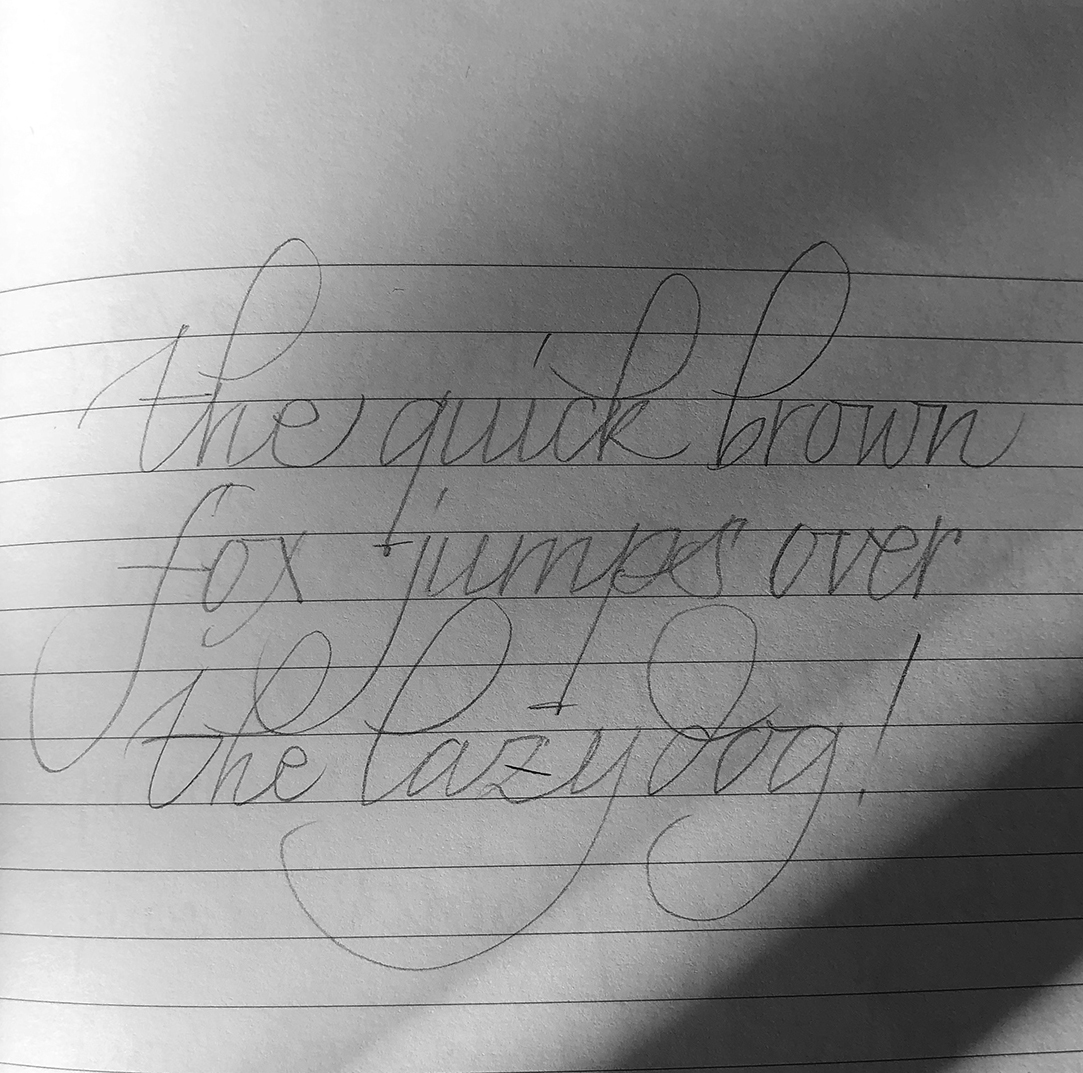
Il piacere di scrivere a mano
Calligrafia con Juls Criveller
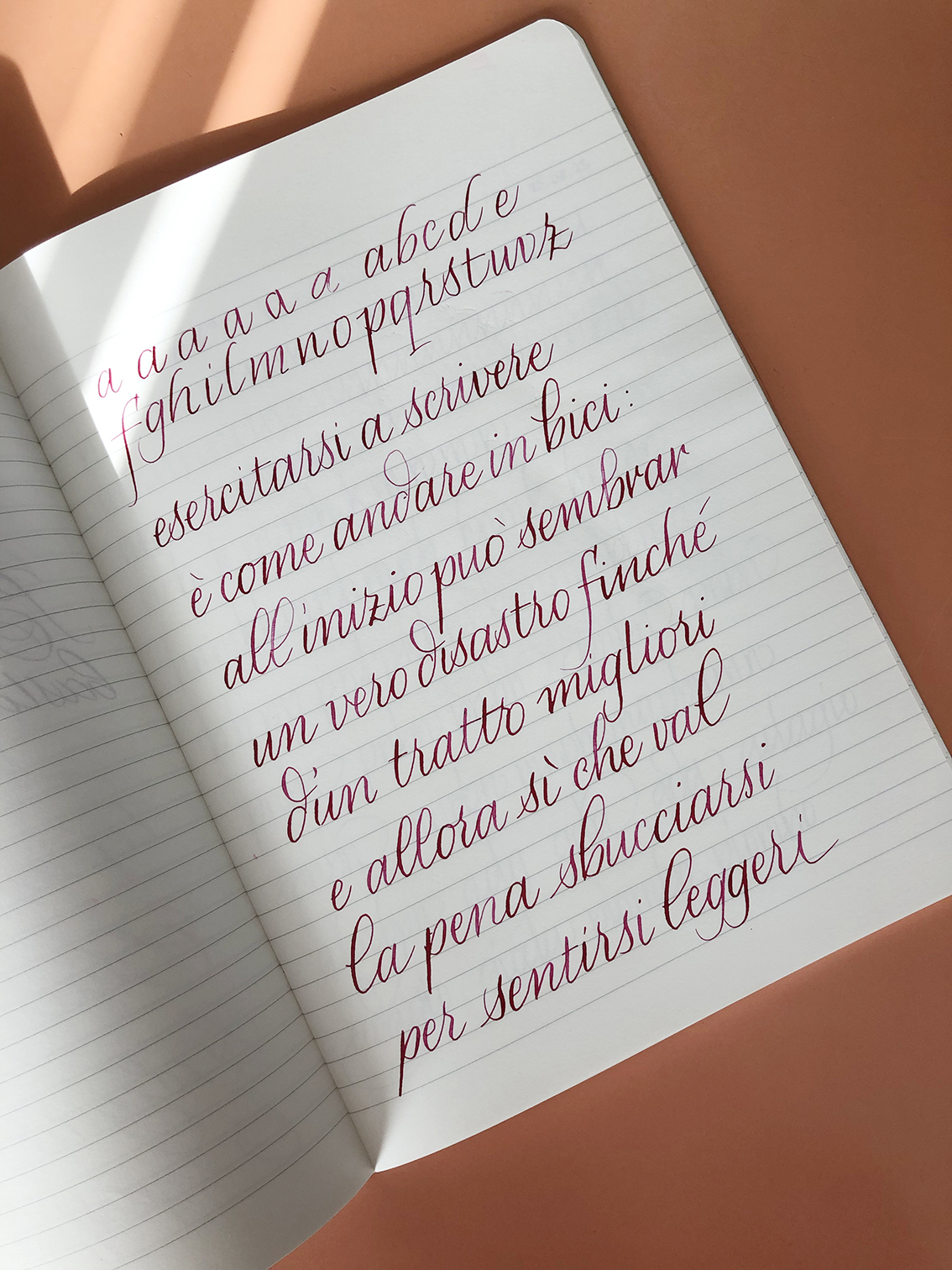
Calligrafia con
Juls Criveller
Un laboratorio dedicato a chi desidera riscoprire il piacere di scrivere a mano e imparare a farlo con eleganza e consapevolezza.
Partiremo dalle basi dell’italico, la scrittura calligrafica che unisce semplicità e bellezza, con esercizi propedeutici che allenano mano, occhio e respiro. Imparerai a riconoscere i movimenti fondamentali e a trasformarli in lettere armoniose e leggibili.
Una volta acquisiti i gesti di base, passeremo alla sperimentazione con diversi strumenti – brushpen e varie tipologie di penne.
Il workshop è pensato per chi non ha alcuna esperienza.
L’obiettivo non è solo “scrivere bene”, ma vivere la scrittura come un momento di calma, creatività e connessione con se stessi.
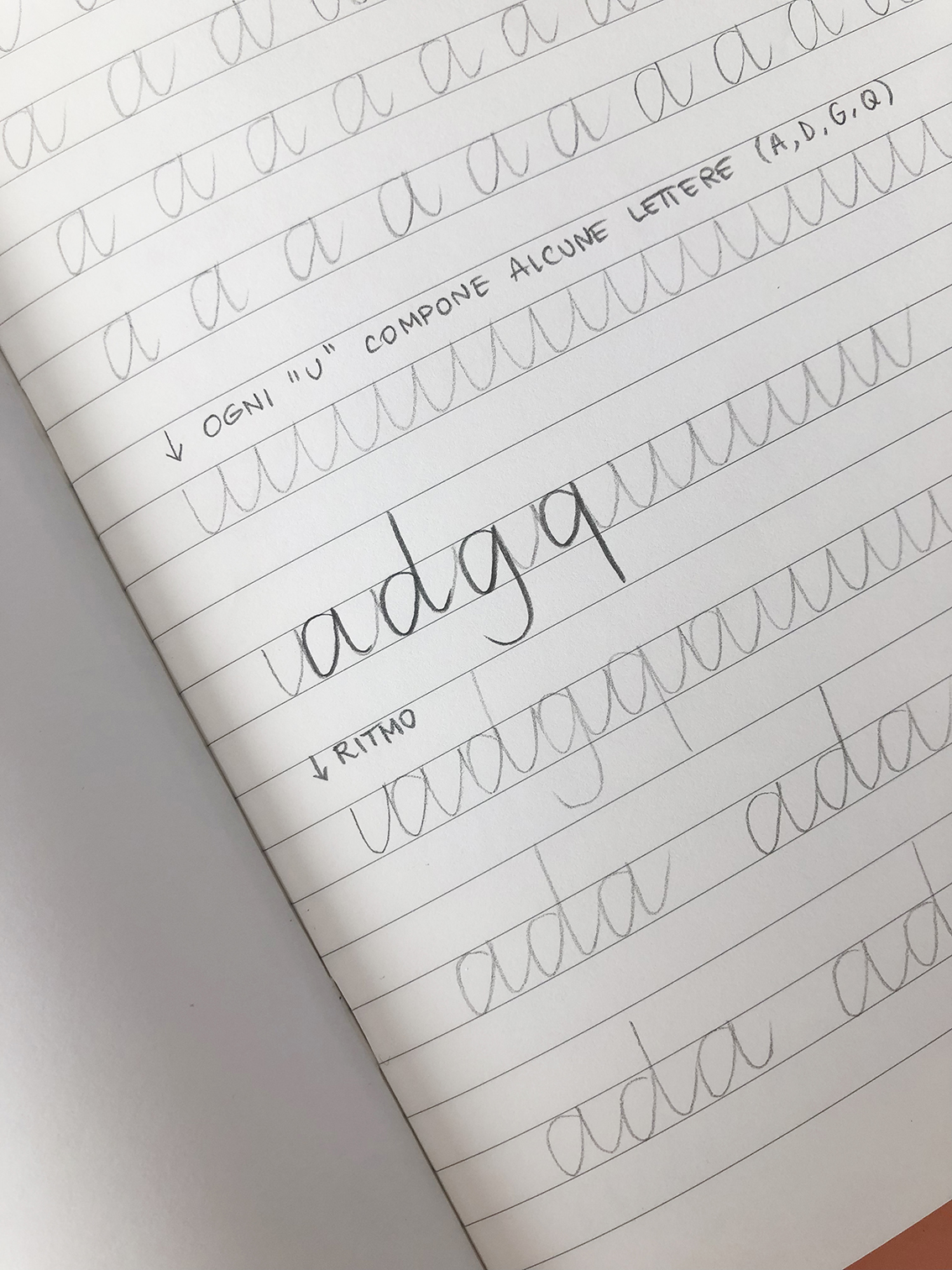
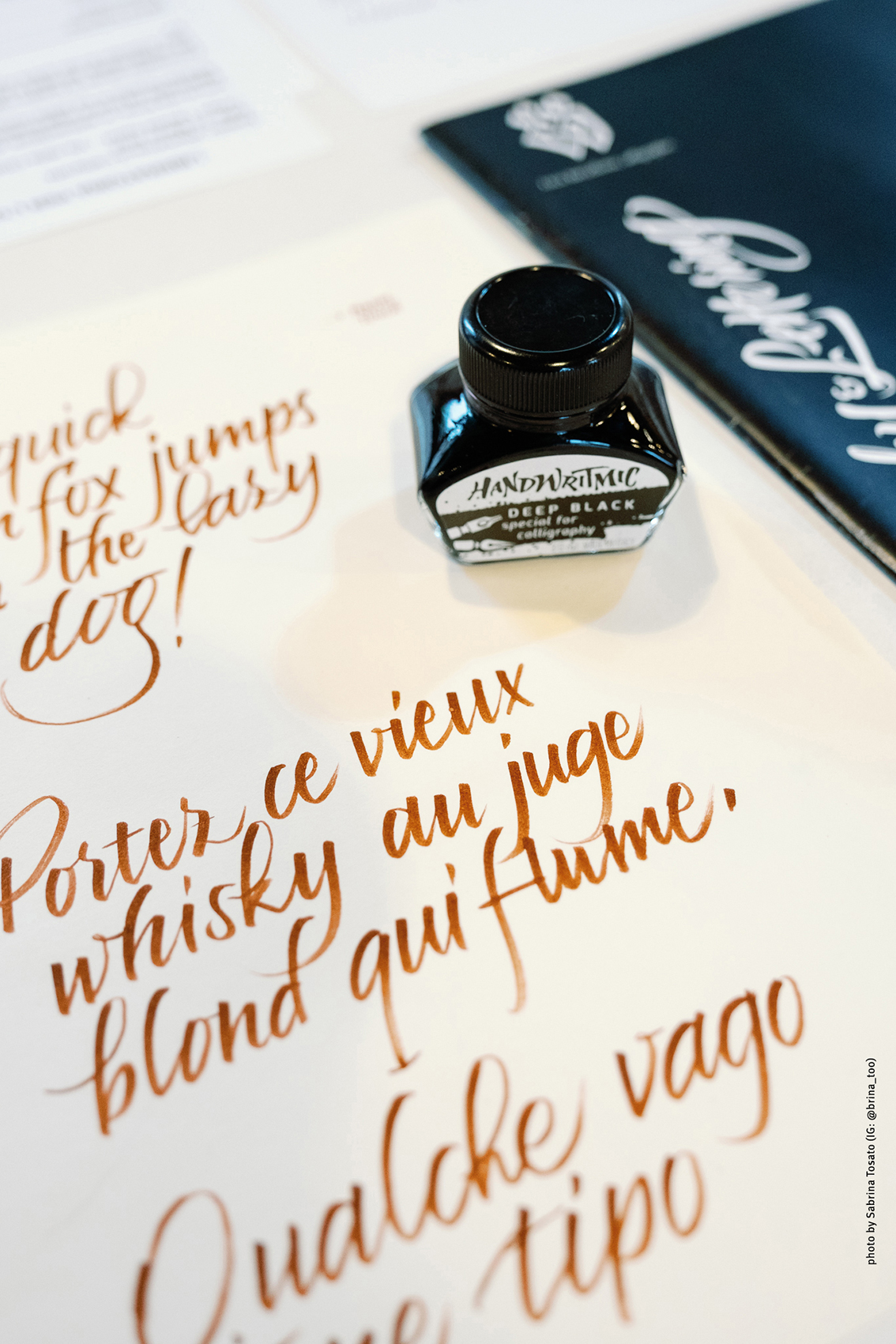
Juls Criveller è una visual designer, specializzata in lettering e illustrazione.
Dopo esperienze come graphic designer e art director per realtà del mondo della comunicazione, dal 2017 ha scelto di lavorare come freelance. Collabora con agenzie e privati per creare progetti personalizzati su grandi e piccole superfici.